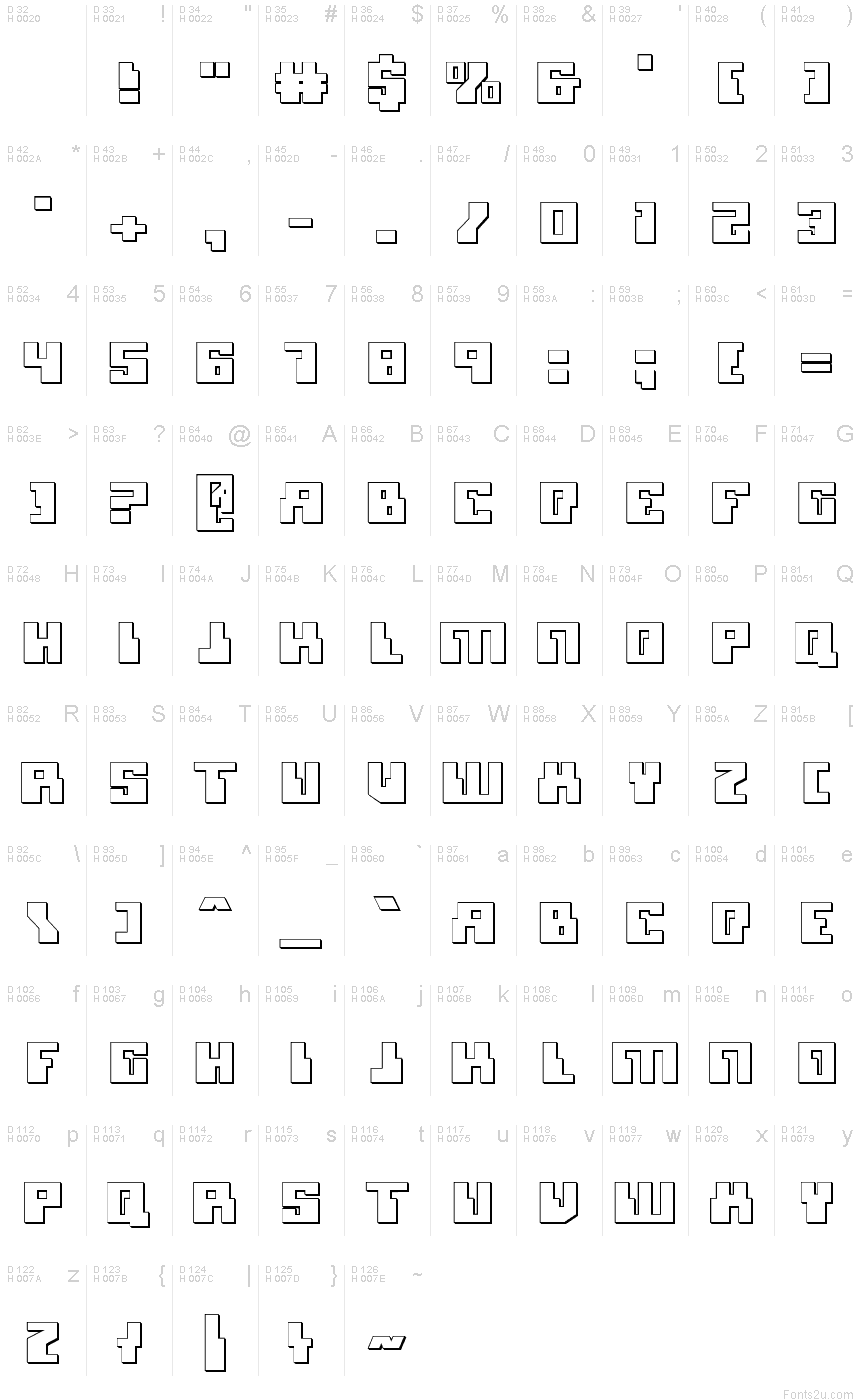
Micronian 3D von Iconian Fonts ist eine kostenlose Techno-Display-Schrift aus quadratischen Großbuchstaben. Durch den versetzten Tiefeneffekt wirken die offenen Umrisse wie massive, gefräste Buchstaben. Die Ecken bleiben hart und geometrisch.
Eine Gaming-Marke oder ein Elektroniklabel könnte die arkadenartige Konstruktion für Logos und Verpackungen nutzen. Sie eignet sich auch für Sci-Fi-Poster und digitale Grafiken, bei denen die gestuften Schatten an Interface-Panels erinnern. Am überzeugendsten wirkt die Schrift in kompakten Titeln, die jeden Buchstaben wie ein gefertigtes Objekt behandeln.
Micronian 3D